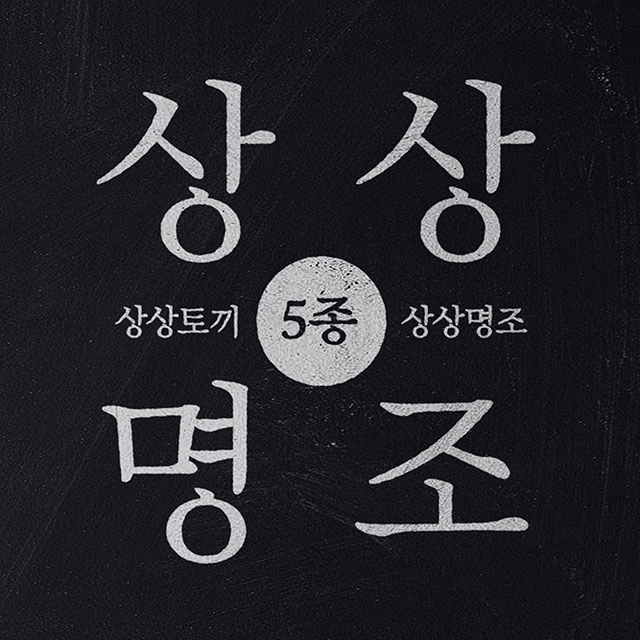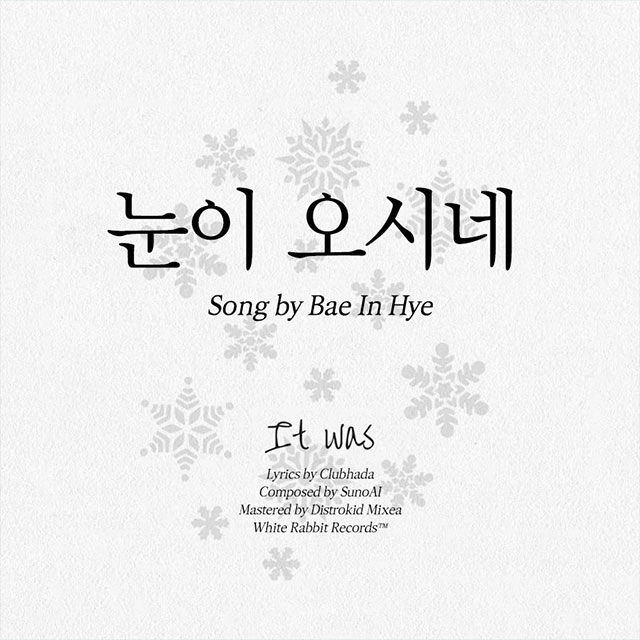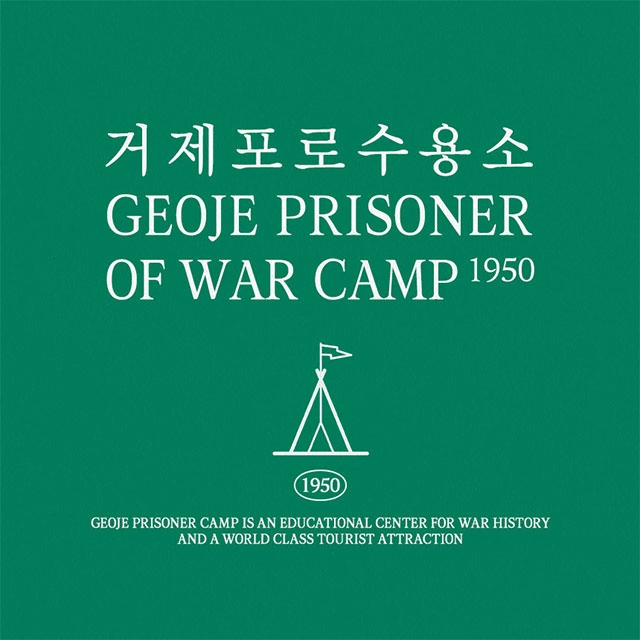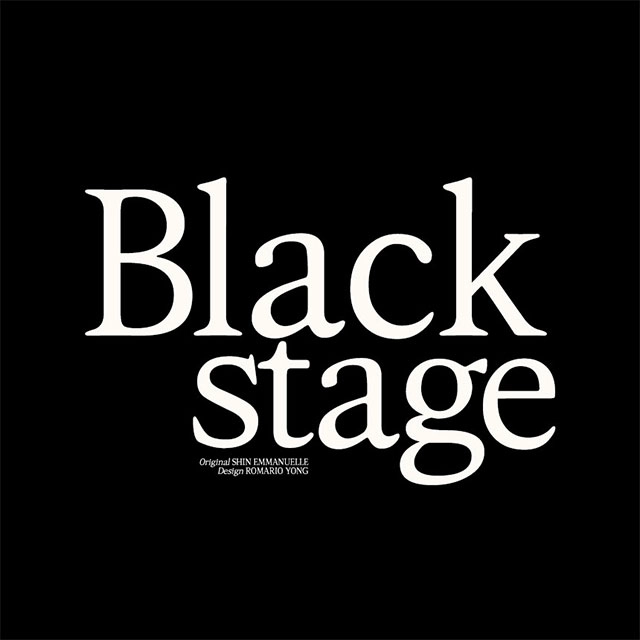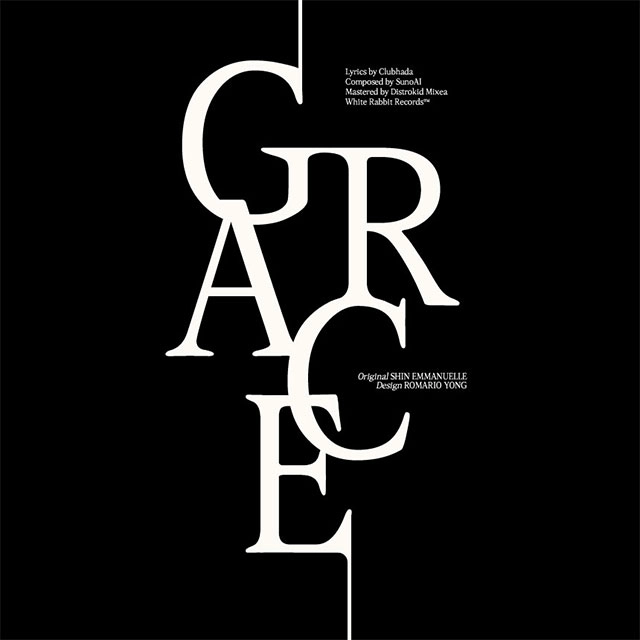
상상명조 5종 UL/L/R/B/EB
상상토끼의 감성과 가독성을 담은 본문용 폰트, 상상명조 5종 UL/L/R/B/EB
글의 기둥, 명조체의 이야기 활자에는 기온이 없다. 그러나 명조체를 바라보고 있노라면 왠지 이른 아침 서늘한 종이의 감촉이 떠오른다. 수묵화처럼 번짐이 깃든 획, 하지만 절도 있는 골격. 명조체는 그렇게, 정갈하지만 따뜻한 목소리로 우리 곁에 오래도록 머물러 있었다.
명조의 기원, 붓에서 활자로 명조체의 기원은 중국 명나라까지 거슬러 올라간다. ‘명조’라는 이름도 바로 그 시대를 따온 것이다. 당시의 간행본들은 주로 나무판을 새겨 찍는 목판인쇄였는데, 이때 등장한 서체가 바로 ‘송체(宋體)’ 혹은 ‘명조체’라 불리는 형태였다.
이 서체는 기존의 흘림 위주였던 서예체에서 벗어나, 인쇄의 효율을 고려해 획을 단순화하고 직선화한 것이 특징이다. 가로획은 가늘고, 세로획은 굵은 대비를 두어 글자의 구조를 안정감 있게 만들었다. 이 구조는 나무판에 새길 때에도 비교적 손상이 적었고, 가독성도 뛰어났다.
▲ 중국 송체(宋體) 예시 이미지
한자 인쇄의 표준이 되다 이후 명조체는 동아시아 전역으로 퍼져나가며 한자 인쇄의 ‘기본 서체’로 자리잡는다. 조선에서도 금속활자가 발달하면서 명조체는 출판물의 표준 서체로 채택되었고, 활판 인쇄 시대 내내 가장 흔하게 볼 수 있는 활자체로 자리잡았다.
▲ 목판 인쇄본 예시 이미지 그리하여 오늘날 우리가 보는 교과서, 신문, 서적의 본문 대부분이 명조의 후예라 해도 과언이 아니다. 글을 담는 그릇으로서의 글꼴, 그 역할에 가장 충실한 서체가 바로 명조체였던 셈이다.
디지털 시대의 명조, 그리고 새 얼굴들 한글의 명조체는 일본 메이지 시대의 ‘민초(明朝, みんちょう)’를 기반으로 형성되었다. 일본에서 서양식 활판 기술을 받아들이며 만든 ‘고식쿠(Gothic, ゴシック)’와 ‘민초’는 한자 문화권의 인쇄 미감을 이끌었다. 한글도 이 영향 아래에서 디지털 폰트 시대에 명조체의 구조와 미감을 받아들이게 된다.
▲ 일본 민초(明朝, みんちょう) 예시 이미지 하지만 디지털 시대가 열리며, 활자의 세계도 변하기 시작한다. 이제는 종이에 인쇄되는 것만이 아니라, 스크린에 어떻게 보일지를 더 고민하게 되었다. 해상도, 눈의 피로도, 디바이스 환경에 따라 명조체도 점점 다양한 얼굴로 바뀌어 간다. 때로는 더 부드럽게, 때로는 더 견고하게. 그 변화의 시간 속에서, 우리는 다시금 묻게 된다. "본문이란 무엇인가?" 그리고 "명조체는 어디까지 명조체일 수 있을까?"
명조체의 주요 특징 3가지 명조체 본문 폰트는 긴 글을 편안하게 읽을 수 있도록 돕는 구조적 안정성과 시각적 리듬을 갖춘 서체로, 정보에 신뢰를 더하고 글에 깊이를 부여하는 활자이다. 그 특징을 정리하면,
상상명조, 나만의 명조체를 꿈꾸며 나는 명조체를 새롭게 해석하고 싶었다. 단정함을 유지하되, 더 따뜻한 결을 넣고 싶었다. 정보 전달을 최우선으로 하되, 읽는 사람의 감정에 조심스럽게 닿기를 바랐다.
▲ 상상명조로 조판한 예문 그렇게 상상명조는 태어났다. 수많은 명조의 계보 속에서, 나만의 감각을 더한 활자. 그것이 앞으로 상상토끼 폰틀리에의 본문을 책임질 시그니처 폰트가 된다면, 그보다 기쁜 일이 없을 것이다.
상상명조의 조형적 특징 상상명조는 절제된 획 대비와 부드럽게 마감된 세리프, 안정된 자소 구성으로 이루어진 본문용 명조체로, 긴 글에서도 편안한 리듬을 유지하며 조용하지만 단단한 인상을 전하는 서체이다.
1. 선명한 획 대비, 한
상상명조는 전통 명조체의 가장 기본적인 조형 원칙인 가로와 세로의 굵기 대비를 분명히 유지하면서도, 그 안에서 부드러운 흐름을 추구한다. 세로획은 굵고, 가로획은 상대적으로 가늘게 설계되어 있어, 전체적으로 안정감 있는 구조를 형성하면서도 시선이 자연스럽게 아래로 흐르도록 유도한다. ‘한’의 ㅎ·ㄴ처럼 세로 방향이 강조되는 자소에서 그 특징이 뚜렷하게 드러난다.
2. 낮은 대비의 일관성 유지, 글
상상명조는 명조체의 핵심인 획 대비를 유지하면서도, 극단적인 굵기 차이를 피하고 전체적인 흐름의 일관성에 집중했다. 이를 통해 긴 본문에서도 글자의 리듬이 불규칙하게 요동치지 않고, 안정적이고 편안한 읽기 경험을 제공한다. ‘글’의 ㄱ 가로획은 얇게 처리되어 시선의 흐름을 자연스럽게 유도하고, ㄹ의 세로획은 굵고 힘 있게 설계되어 글자 전체의 구조를 단단하게 지탱한다.
3. 유려한 곡선의 흐름, 정
상상명조는 단순한 직선과 곡선을 나열하는 데 그치지 않고, 획과 획이 이어지는 곡률의 흐름을 유기적으로 설계했다. 이로 인해 글자의 각 부분이 마치 살아 있는 듯 자연스럽게 이어지고, 전체 문장에서 부드러운 리듬감을 형성한다. ‘정’의 ㅈ이나, ‘한’의 ㅎ 곡선에서 흐름이 멈추지 않고 이어지는 조형이 인상적이다.
4. 부드러운 말단 처리, 체 (소프트 세리프)
기존 명조체에서 흔히 볼 수 있는 날카롭고 직선적인 세리프 대신, 상상명조는 획 끝을 매끄럽게 말아주는 방식으로 처리해 더욱 유연하고 따뜻한 인상을 준다. 이처럼 날이 서지 않은 세리프는 본문용 활자에서 눈의 피로를 줄이고, 서정적인 분위기를 만들어준다. ‘체’의 ㅊ 획 끝에서 볼 수 있듯이, 말단이 둥글게 마무리되어 부드러운 마감 느낌을 준다.
5. 시각 중심을 고려한 배치, 빛
상상명조는 자소들의 위치와 무게 중심을 정밀하게 설계하여, 글자 하나하나가 안정적으로 자리잡고 있는 느낌을 준다. 특히 받침 자소의 크기와 간격은 가독성과 시각 균형을 고려하여 아래로 갈수록 시선을 안정시키는 구조를 띤다. ‘한’의 ㄴ이나 ‘빛’의 ㅊ에서 받침이 전체 글자에 든든한 기반을 제공하는 듯한 인상을 준다.
상상명조 영문의 조형적 특징 상상명조 영문은 전통 세리프의 구조적 품위를 바탕으로, 부드럽게 흐르는 곡선과 절제된 획 대비를 통해 한글 조형과 자연스럽게 어우러지는 균형감 있는 서체이다.
1. 획 대비의 리듬감, HNE
상상명조는 한글에서 수직 강조, 즉 굵은 세로획과 가는 가로획의 대비가 핵심이다. 영문 셰리프도 같은 대비 구조를 가져가면서, 가독성과 단단한 인상을 동시에 유지하고 있다. 한글 ‘글’, ‘한’의 구조적 대비와, 영문 ‘H’, ‘N’, ‘E’의 수직 중심성은 리듬감 면에서 잘 이어진다.
2. 부드러운 말단 처리, ASQ (Soft Serif)
상상명조는 일반 명조체보다 덜 날카롭고 더 따뜻한 곡선형 말단을 갖고 있다. 대표적인 영문 셰리프 Times New Roman보다는 덜 딱딱하고, 살짝 라운딩된 세리프로 처리되어 전반적으로 부드럽고 사람 손의 감성이 느껴지는 조형이다. 특히 ‘A’, ‘S’, ‘Q’ 같은 글자에서 그 부드러움이 시각적으로 통일감을 준다.
3. 가독성을 살린 공간 구조
상상명조는 글자 내부 공간이 넓고, 시원시원한 여백 활용이 돋보인다. 영문도 자간과 내부 공간을 여유 있게 확보해서, 본문에서 장시간 읽어도 피로하지 않게 설계됐다. 이는 한글 ‘체’, ‘빛’의 무게 중심과 자소 간 간격과 매우 잘 어울리는 미감이다.
4. 디지털 시대에 어울리는 고전의 재해석
상상명조는 디지털 환경에서도 유연하게 읽히는 고전 명조의 재해석이다. 이 영문 셰리프 역시 클래식한 구조 안에서 너무 올드하지 않도록 조형을 정제했다. 그래서 둘 다 “디지털 시대의 활자미감”이라는 같은 시대정신을 공유하고 있다. 정갈하지만 따뜻하고, 견고하지만 유연한 — 이 양면성이 한글 상상명조와 이 영문 셰리프를 자연스럽게 연결해주고 있다.
글꼴 미리보기 상상명조를 사용하여 조판한 한글/영문 미리보기 이미지입니다.